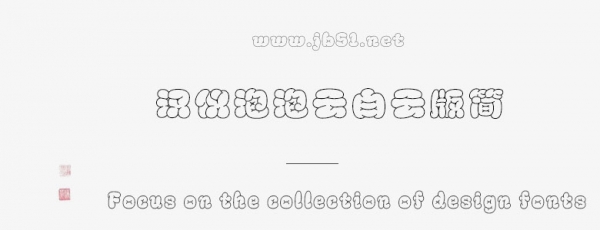
漢儀泡泡云由漢儀字庫出品的藝術(shù)字體,字體以獨特的膨脹表現(xiàn)手法重塑字體,融合云朵的柔軟、泡泡的膨脹和氣球的輕盈,洋溢著潮流有趣的年輕態(tài)度,具有很好的視覺感,適合應(yīng)用于藝術(shù)設(shè)計、平面宣傳設(shè)計、網(wǎng)頁設(shè)計,書法字帖等領(lǐng)域。有需要的朋友快來本站下載使用吧。
漢儀泡泡云以獨特的膨脹表現(xiàn)手法重塑字體,融合云朵的柔軟、泡泡的膨脹和氣球的輕盈,洋溢著潮流有趣的年輕態(tài)度,又帶有一點點來自上世紀70年代街頭涂鴉的復(fù)古氣息。這款字體以平面表現(xiàn)出擠壓膨脹的空間感,獨具柔軟張力的視覺沖擊和豐富的趣味性,適用于年輕化品牌、流行生活方式、旅游出行、戶外運動、潮流玩具及影視娛樂等字體應(yīng)用場景,呈現(xiàn)滿滿的輕盈和松弛。
為適應(yīng)不同環(huán)境的使用,漢儀泡泡云分為兩個版本:藍天版和白云版。線條構(gòu)成的藍天版透過文字輪廓突出背景,填充白色的白云版讓文字如同云朵飄浮在背景前。
質(zhì)感蓬松、類似棉花糖的“泡泡字”起源于20世紀70年代的紐約街頭涂鴉,是一種名為Throw-ups的涂鴉形式,又稱Throwie。漢儀泡泡云大膽地在中文字體設(shè)計中繼承了這種涂鴉形式的藝術(shù)基因。
漢儀泡泡云,字形飽滿,大小一致,線條清晰均勻,膨脹的筆畫將字內(nèi)負空間壓縮到最小。
采用夸張設(shè)計手法的同時保證漢字字形的規(guī)范性與識讀性,原則上筆畫不作減省,筆畫之間為擠壓而非疊壓關(guān)系,部分復(fù)雜字形有特殊處理。
不同于常規(guī)以筆畫為基礎(chǔ)的字體設(shè)計,漢儀泡泡云是將整個字形作為圖形而設(shè)計的,筆畫的膨脹和擠壓自然生動,趣味十足。
漢儀泡泡云的漢字比例較為扁寬,西文單個字母比例也較常規(guī)略扁寬。
西文字符之間做了擠壓的效果,使字母組合的復(fù)雜程度接近單個漢字字符,同時縮短單詞的長度以獲得流暢的閱讀體驗。